Font racing memiliki bentuk yang sangat khas. Dengan garis-garis tegas dan gaya italic, font racing cocok untuk digunakan dalam desain-desain yang terkait dengan dunia otomotif, balap, dan kecepatan. Kehadirannya memberikan sentuhan energik sekaligus kece pada proyek desain Ana.
Namun, penggunaannya pun semakin meluas, tidak hanya terbatas pada desain acara balap, tetapi juga cocok untuk berbagai jenis desain seperti logo, merchandise, dan desain grafis lainnya. Nah, apabila Anda sedang mencari font racing gratis, dalam artikel ini, kami menyediakan 37 rekomendasi font racing keren yang bisa langsung Anda unduh dan gunakan secara gratis untuk mempercantik desain Anda. Yuk, simak kumpulan font nya di bawah ini!
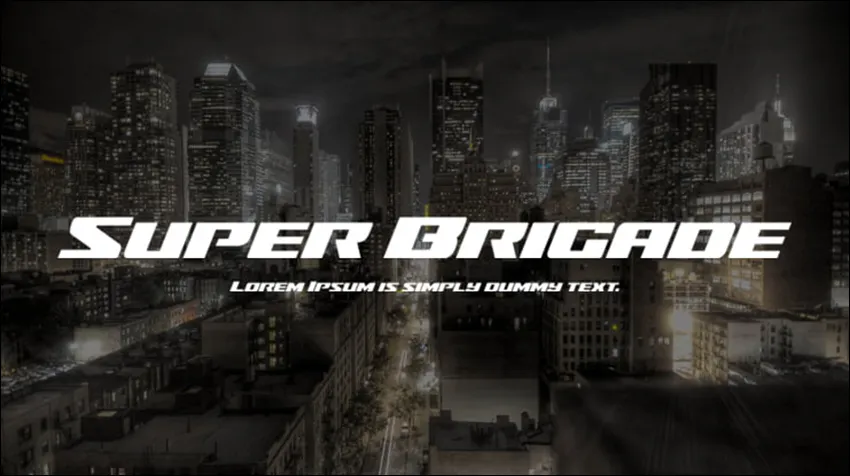
Font pertama adalah Super Brigade, font racing dengan bentuk huruf yang kuat dan tebal, cocok untuk menonjolkan kesan kecepatan dan keberanian pada desain poster atau merchandise dengan tema yang beragam.
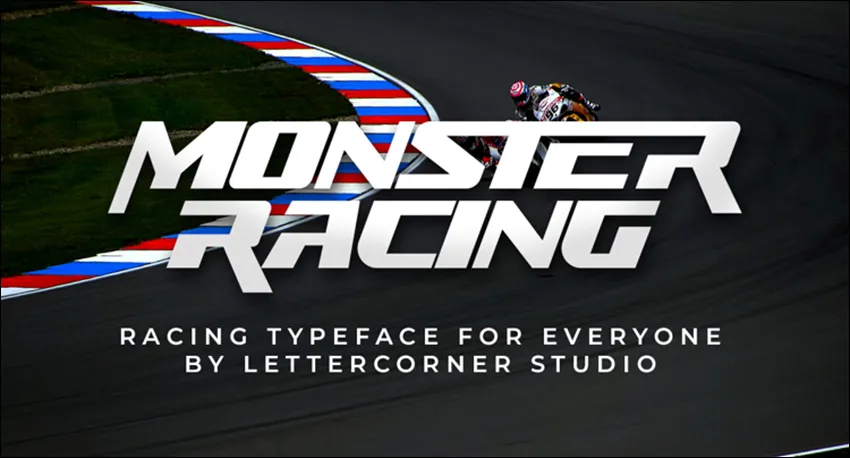
Font kedua adalah Monster Racing, font yang memiliki desain bold, keren, dan modern, cocok digunakan dalam desain-desain yang membutuhkan sentuhan yang kuat dan dinamis, baik itu untuk balapan maupun desain lainnya seperti merchandise.
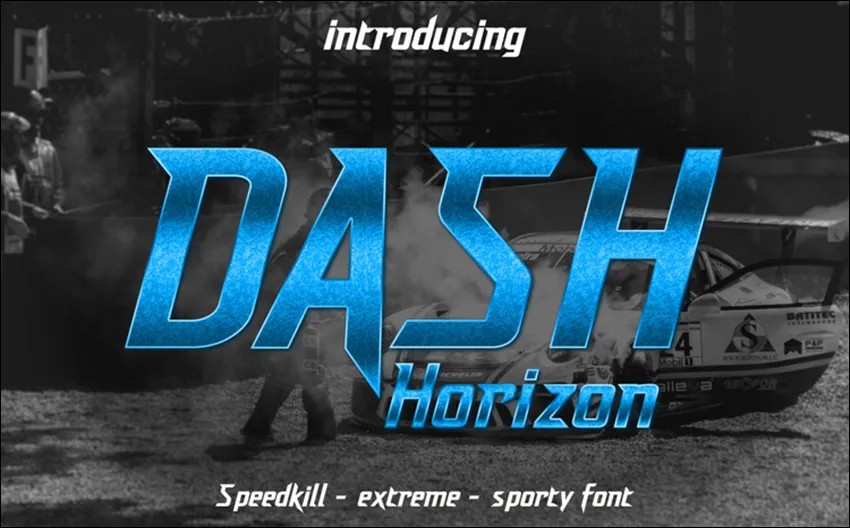
Selanjutnya adalah Dash Horizon, font racing yang menampilkan huruf-huruf yang modern dengan sudut-sudut tajam dan gaya futuristik, cocok untuk digunakan dalam berbagai desain yang membutuhkan kesan modern dan inovatif, baik itu poster, merchandise, atau materi promosi lainnya.
Brake Disc menampilkan huruf-huruf yang terinspirasi dari bentuk-bentuk mekanis, memberikan kesan teknologi dan kecepatan yang cocok untuk digunakan dalam desain-desain yang berhubungan dengan balapan maupun desain-desain otomotif lainnya.
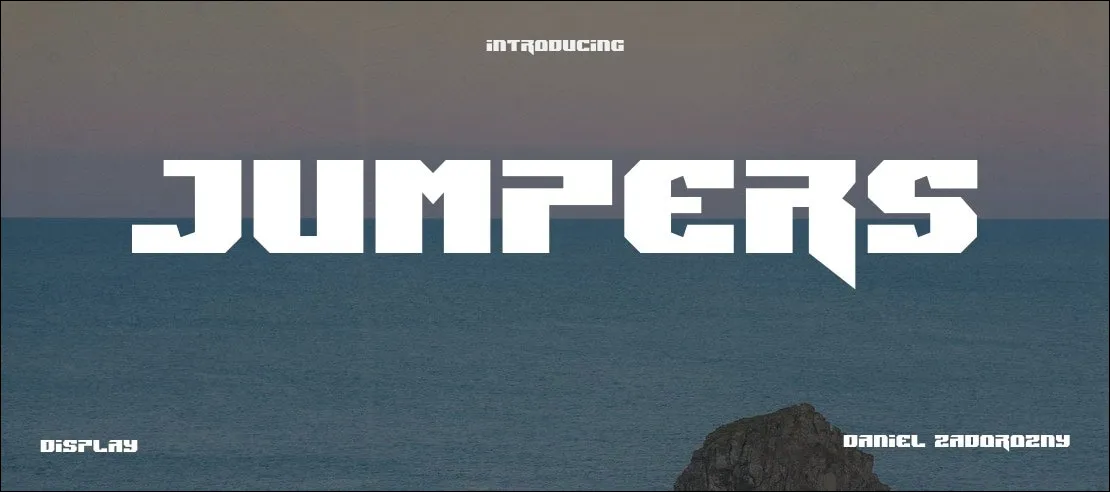
Jumpers memiliki bentuk huruf yang dinamis dan mewah dengan sudut-sudut yang melengkung, cocok untuk digunakan dalam desain poster, merchandise, atau materi promosi lainnya.
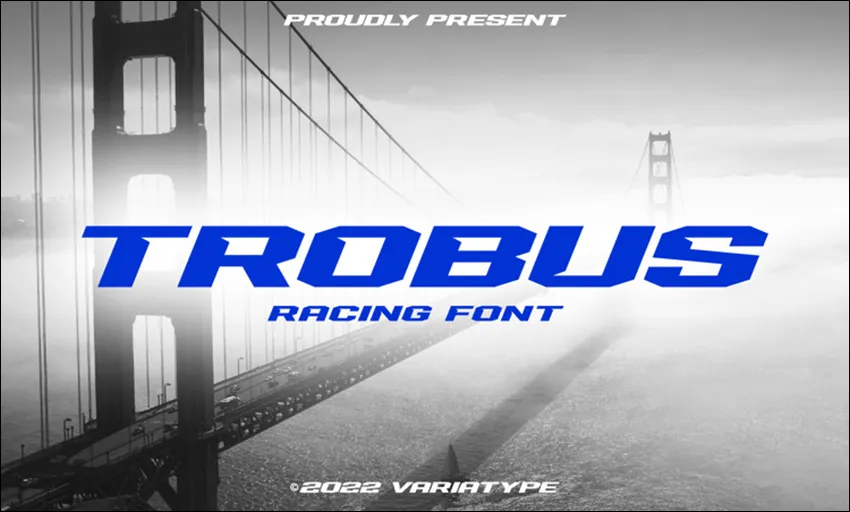
Trobus Expanded menampilkan huruf-huruf tebal dengan gaya techno, cocok untuk berbagai desain, tidak hanya dalam desain balapan tetapi juga desain-desain lainnya.
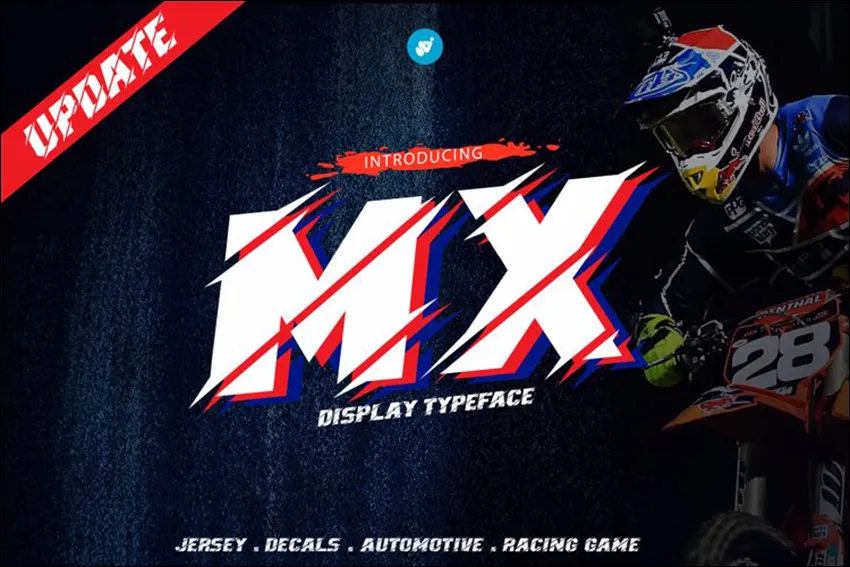
MX menampilkan huruf-huruf bold modern dengan sudut-sudut tegas, cocok untuk digunakan dalam desain-desain cover majalah otomotif, game balap, logo dan branding, desain produk, label, dan lain-lain.
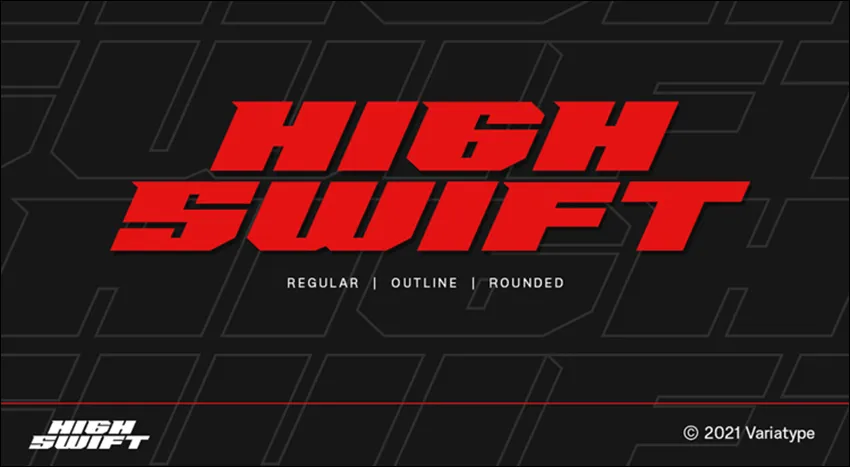
High Swift menampilkan huruf-huruf yang dinamis dan sporty, cocok digunakan untuk branding perusahaan, iklan, logo, dan banyak lagi.
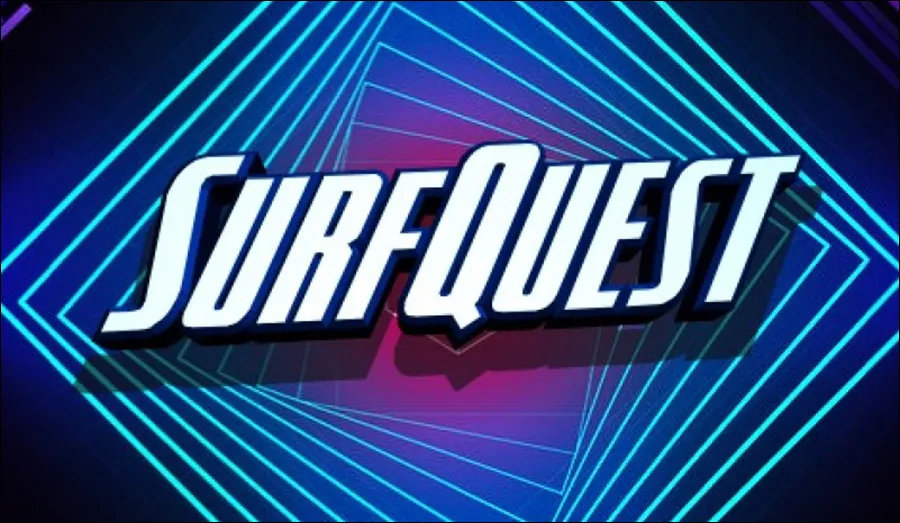
SurfQuest menampilkan huruf-huruf yang ramping dan tinggi, cocok untuk digunakan dalam desain-desain poster, merchandise, atau materi promosi lainnya.
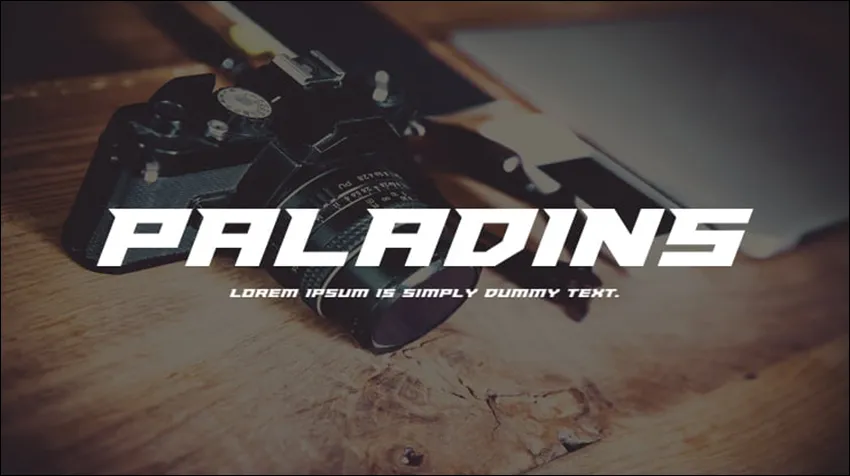
Paladins memiliki bentuk huruf dengan desain techno, cocok untuk digunakan dalam desain-desain balapan dan yang lainnya.
Bigail menampilkan huruf-huruf yang tebal dan berkontur tegas dengan gaya retro, cocok digunakan dalam desain-desain yang ingin menampilkan kesan klasik yang timeless, baik itu poster, merchandise, atau materi promosi lainnya.
Font ini memiliki desain yang kreatif dan kontemporer, cocok digunakan untuk headline balapan, proyek branding, iklan, kemasan produk, desain produk, label, dan lain sebagainya.
Star 7 memiliki desain mewah, bold, dan modern, cocok untuk digunakan dalam desain-desain logo, branding, fotografi, kutipan, header blog, poster, iklan, sampul buku, dan lain-lain.
Race Sport menampilkan huruf-huruf techno modern dengan gaya yang unik, cocok untuk digunakan dalam desain-desain yang ingin menonjolkan tema olahraga dan kecepatan, baik itu balapan maupun desain-desain lainnya seperti merchandise.
Spiky-016 menampilkan huruf-huruf yang berkontur tegas dengan ujung-ujung yang runcing, memberikan kesan agresif dan dinamis yang cocok untuk digunakan dalam desain-desain balapan dan lainnya.
Brave Phoenix menampilkan huruf-huruf yang kokoh dan berani sekaligus memberikan kesan futuristik, cocok untuk digunakan dalam desain poster, merchandise, atau lainnya.
Dengan huruf-huruf italic yang sederhana namun dinamis dengan sudut-sudut yang tegas, font ini cocok untuk digunakan dalam berbagai desain dengan tema yang beragam, mulai dari balapan hingga desain-desain lainnya seperti merchandise, poster, dan lain sebagainya.
Sacred Czars memiliki desain huruf yang bold dan elegan, cocok untuk digunakan dalam desain poster, merchandise, label, dan yang lainnya.
Font racing menghadirkan semangat kompetitif dan kecepatan yang tidak hanya terkait dengan balapan, tetapi juga cocok untuk berbagai jenis olahraga yang menuntut kelincahan, seperti sepak bola, basket, atau skateboarding.